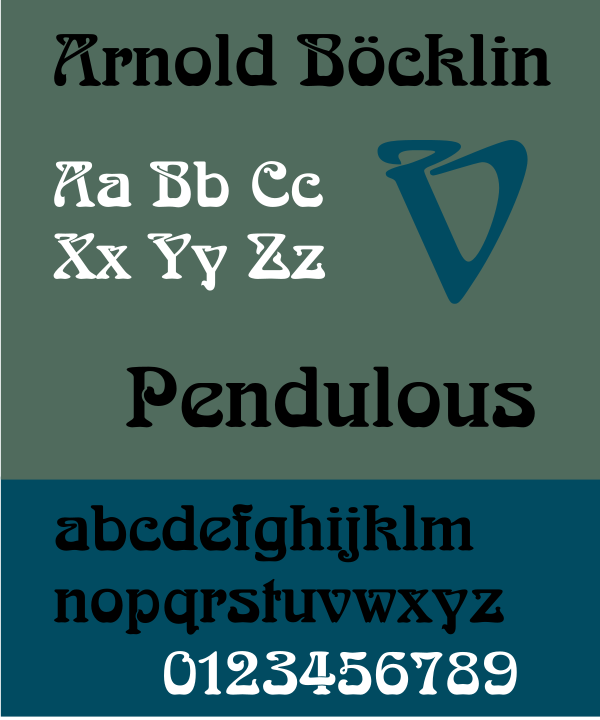
Arnold Böcklin (шрифт)
Arnold Böcklin — шрифт, разработанный в 1904 году в словолитне Отто Вайсерта в немецком Штутгарте. Шрифт был назван в память о швейцарском художнике Арнольде Бёклине, умершем в 1901 году. Дизайнер, разработавший шрифт, остался неизвестным[1].
Шрифт в стиле модерн. В шрифте Arnold Böcklin можно увидеть следы цветочных форм югендстиля. Шрифты такого типа в основном предназначались для набора заголовков на плакатах. Декоративное ощущение было гораздо важнее, чем удобочитаемость, и Arnold Böcklin имел особое значение для дизайна книг движения югендстиль[2]. Arnold Böcklin пережил ренессанс в 1960-х и 1970-х годах в свете общего возрождения стиля модерн в популярном дизайне. Его влияние можно увидеть в работах таких иллюстраторов, как Роджер Дин и стакиста Пола Харви.
| Стиль | с засечками |
| Дата создания | 1904 |
| Дизайнер | Отто Вайсерт |
| Словолитня | Mergenthaler Linotype Company[d] |
Из-за включения этого шрифта в ранние версии CorelDRAW под названием Arabia, он часто в самых разных контекстах использовался в восточной тематике, не имея ничего общего с каллиграфией арабского алфавита.
Шрифт использовался в титрах телесериала «Шоу 70-х». В 1989 году Data East использовали шрифт на главном экране компьютерной игры Hippodrome. Этим шрифтом также писалось название журнала White Dwarf с конца 1970-х до начала 1980-х годов.
Шрифт использовался на обложке студийного альбома Back to Bedlam Джеймса Бланта, альбома Every Good Boy Deserves Favour группы The Moody Blues, первого альбома Emergency on Planet Earth группы Jamiroquai, а также на альбомах Dinosaur Jr..